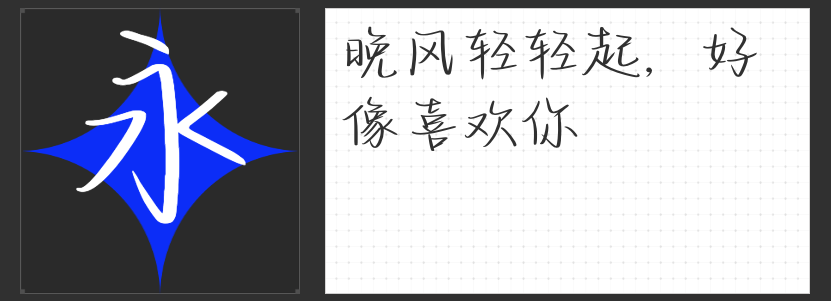
让广告“小清新”,用这四款手写字体试试吧
在广告设计中,字体的选择往往决定了作品的风格和氛围。对于追求“小清新”风格的广告来说,手写字体无疑是最佳选择之一。今天,我将为大家推荐四款适用于小清新广告设计的手写字体,它们各具特色,能够让你的设计作品更加生动有趣。
1️⃣ 小豆岛默陌秀丽简
纵情释放你的文艺气息吧!这款字体笔锋有力,每一笔每一划都透露出传统书法的写意风格。点划看似随意,却又不失整体疏密有致的美感。通过巧妙的节奏塑造线条粗细和节点,这款字体能够很好地传达出广告中的文艺和雅致气息,是设计文艺类广告的不二之选。
2️⃣ 小豆岛默陌肥圆手写简
治愈一切不开心。这款字体字形丰腴圆润,采用轻松自由的水墨笔触,笔画节点随性而不拘小节,让人一眼就能感受到温暖和治愈的力量。它的应用性强,可以随意拉伸使用,非常适合设计那些需要传达温馨、治愈氛围的广告。
3️⃣ 字圈也字夏夜晚风体
这款字体从字形结构上,横斜竖直,左低右高,折笔处大为钝角,小为直角。棱角时而圆润,时而尖锐,透露出一种坚定而自信的走向。使用这款字体设计的广告,能够展现出一种不在乎他人看法,遵从自我内心的态度,非常适合设计那些需要传达个性、自信的广告。
4️⃣ 小豆岛默陌写意水墨简
清雅含蓄的传统与现代结合。这款字体笔尾锋芒,笔触潇洒,既有传统书法的写意韵味,又融入了现代手写的俏皮元素。线条富有节奏与灵气,点缀生动,具有浓郁的水墨特点。使用这款字体设计的广告,能够很好地展现出传统与现代的交融之美,让人眼前一亮。
这四款手写字体各具特色,适用于不同风格的小清新广告设计。希望它们能够成为你设计路上的得力助手,让你的作品更加出彩!